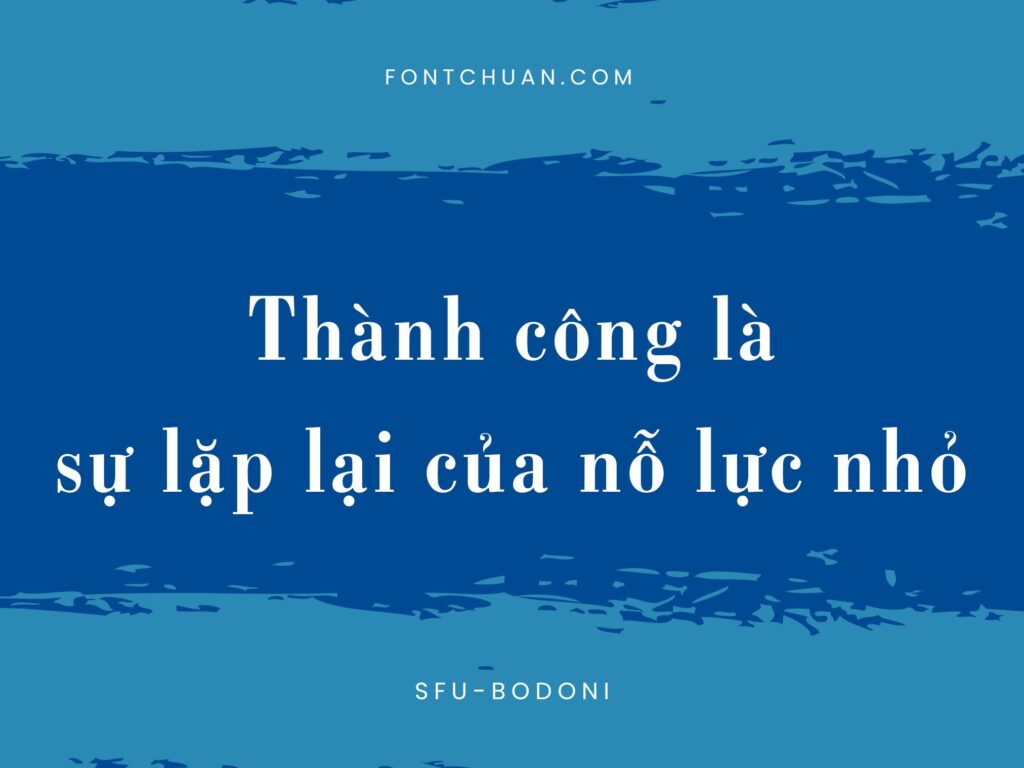
Font Bodoni là một kiểu chữ serif cổ điển, được thiết kế bởi Giambattista Bodoni vào cuối thế kỷ 18. Với sự tinh tế và độ tương phản cao giữa các nét chữ, Bodoni mang lại cảm giác thanh lịch và hiện đại, phù hợp cho nhiều mục đích thiết kế khác nhau như in ấn, xuất bản và thiết kế kỹ thuật số. Font này hỗ trợ đầy đủ tiếng Việt, giúp người dùng dễ dàng ứng dụng trong các dự án đa ngôn ngữ
Về đặc điểm thiết kế, Bodoni thuộc nhóm font serif với các nét chữ rõ ràng, độ tương phản cao giữa nét thanh và nét đậm, cùng với các chân chữ (serif) sắc nét và tinh tế. Kiểu chữ này rất phù hợp để sử dụng trong các thiết kế như sách, tạp chí, thiệp mời, logo và các ấn phẩm quảng cáo